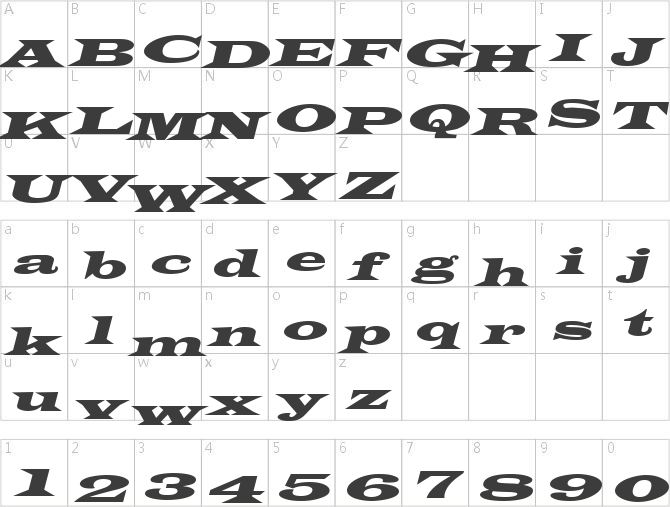
Latin-WideExtObl-Normal(1) 詳情頁
字體名稱: Latin-W
Latin-WideExtObl-Normal(1)
Latin-WideExtObl-Normal(1)字體字庫是一款讓人賞心悅目、百看不厭的英文字體,適合各類廣告和產品包裝設計應用,字體大小0.04MB,格式為ttf字體,上傳用戶是23KUN,作者/版權方為未知